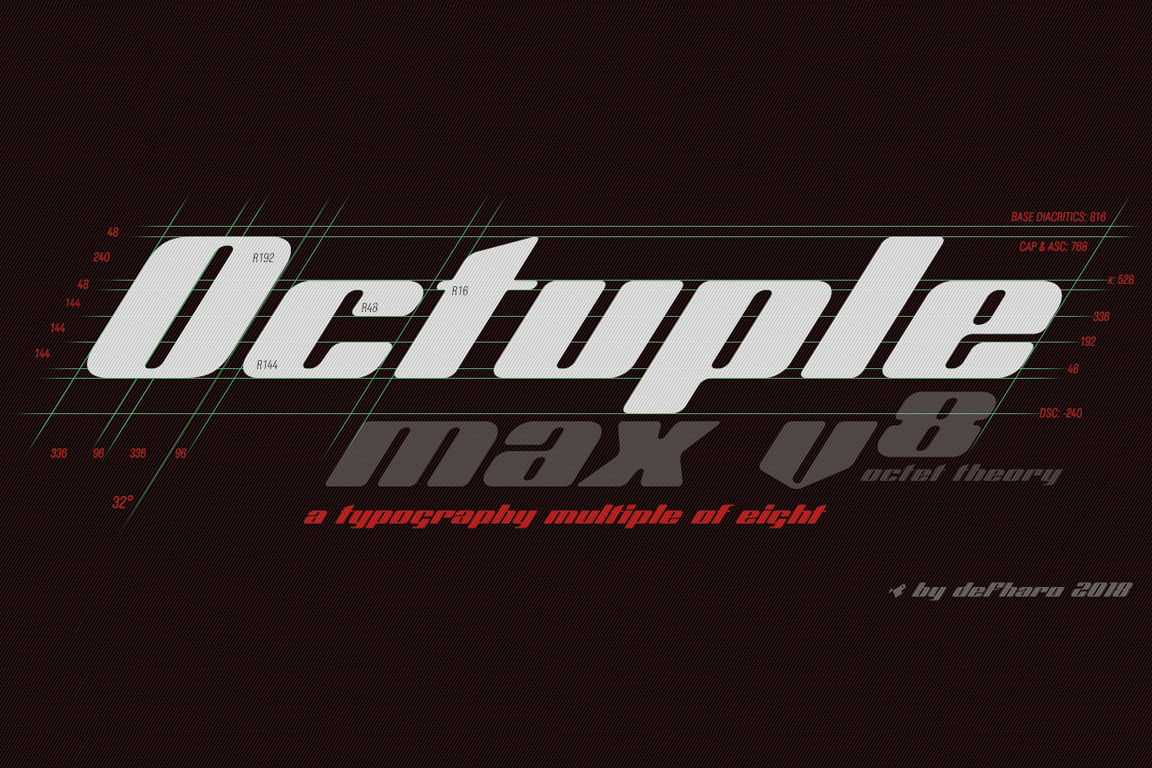
A Octuple Max é uma experimentação tipográfica onde todas as proporções e medidas dos caracteres e métricas são múltiplas do número oito. O resultado é um tipo muito inclinado, com proporção quadrada, repleto de contraste entre os cornos horizontais/verticais e suaves em todos os cantos. Esta fonte única tem uma consistência de design que se destaca por seu desafio inovador às normas convencionais de proporções tipográficas. Ela é perfeita para criar texturas dinâmicas, especialmente no design gráfico contemporâneo e no design web onde a transparência visual pode fazer toda a diferença na experiência do usuário. A Octuple Max oferece uma ferramenta valiosa para designers inovadores que buscam adicionar um toque único à sua obra.